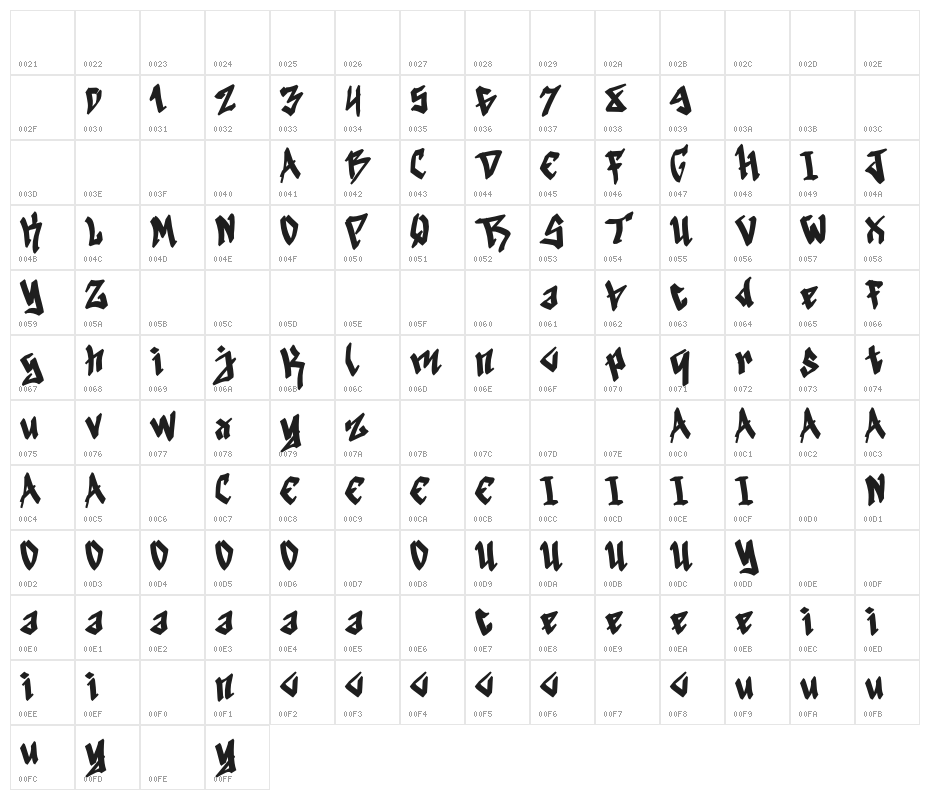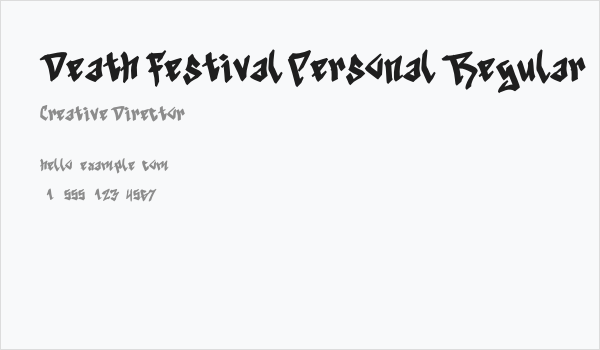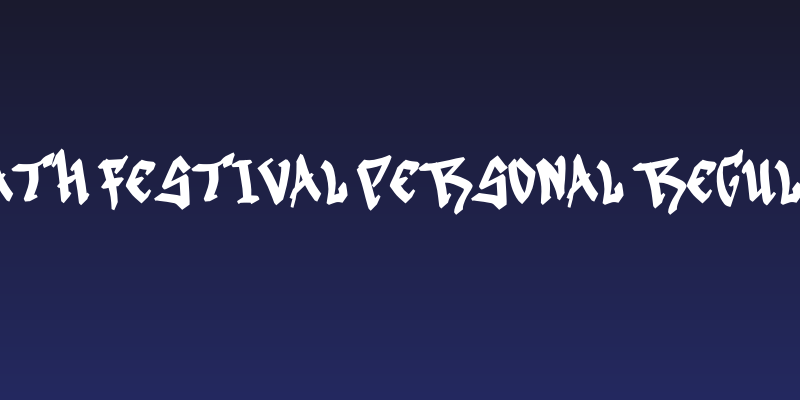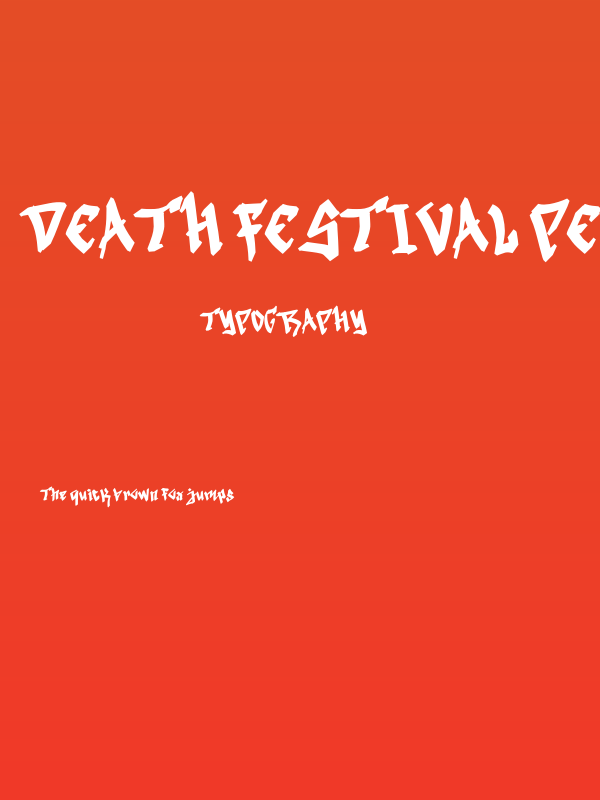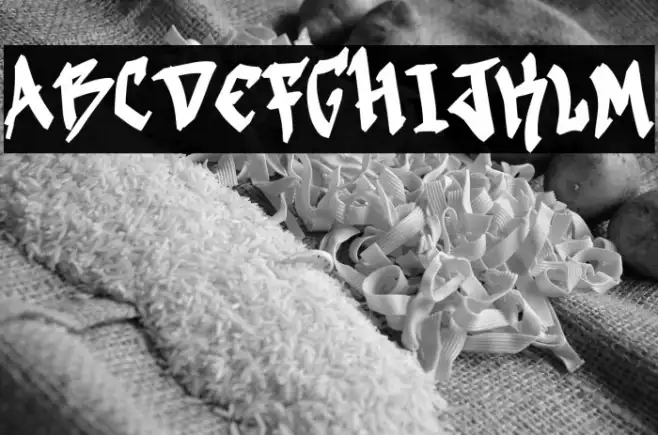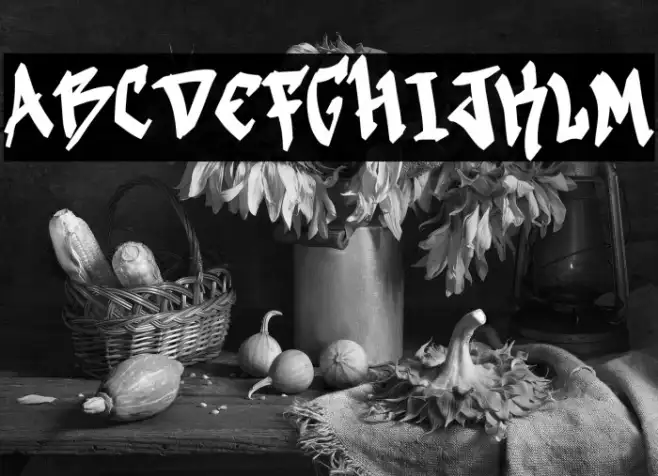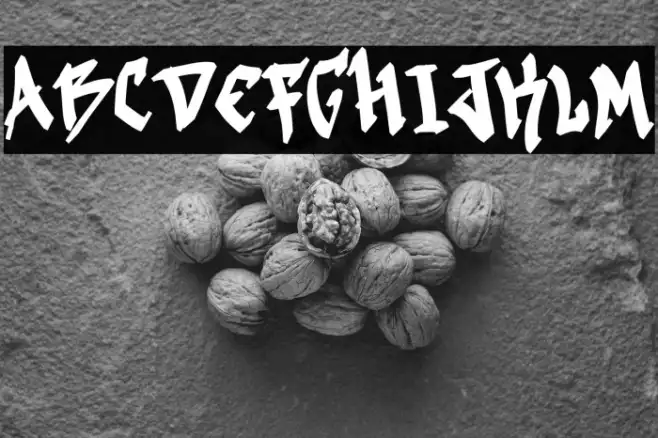
Death Festival Personal Regular Font
✎ Gothic
| Gesamtstil | Gothic, Dramatic, Edgy |
| Anwendungsfall | Headlines, Posters, Branding |
| Vorgeschlagene Projekte | Ideal for music festival posters, edgy branding, or Halloween-themed designs. |